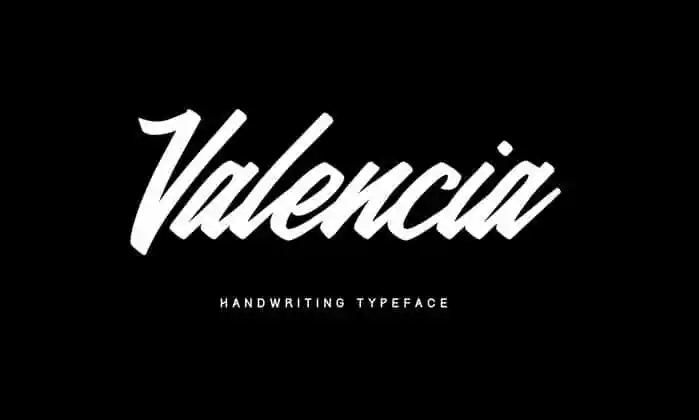
Valencia Calligraphy Font
Introduzimos Valencia Calligraphy Font! Desenvolvida e compartilhada pelo designer Graphicpear, Valencia Script é uma fonte de escrita calligráfica que traz um rico legado ao design digital. O termo “calligraphia” vem do grego e significa “escrita bela”. As fontes de escrita calligráfica são desenhadas para imitar a elegante, precisa e levemente qualquer tipo de escrita humana de maneira incrivelmente realista. Valencia Calligraphy Font adiciona um toque de estilo e muito variabilidade às suas projetos de design. Com seu traço único e arredondado, ela torna os seus trabalhos mais atraentes e distintivos. Seja para títulos ou corpos de texto, Valencia Script é perfeita para criar designs que despertem interesse visual. Se você está procurando por uma fonte que ofereça tanto estilo quanto versatilidade, então não deixe de experimentar Valencia Calligraphy Font. Com certeza ela será sua escolha favorita!